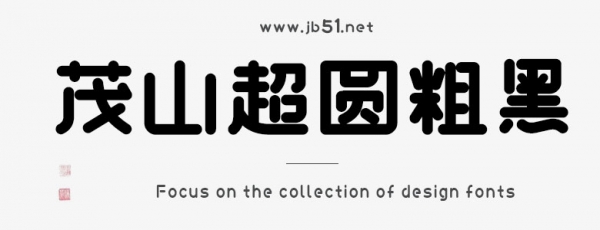
茂山超圓粗黑是Aa字庫(kù)推出的藝術(shù)字體,字體筆觸粗實(shí),字形端正,具有很好的視覺(jué)感,適合應(yīng)用于藝術(shù)設(shè)計(jì)、平面宣傳設(shè)計(jì)、網(wǎng)頁(yè)設(shè)計(jì),書(shū)法字帖等領(lǐng)域,歡迎需要的朋友下載使用。